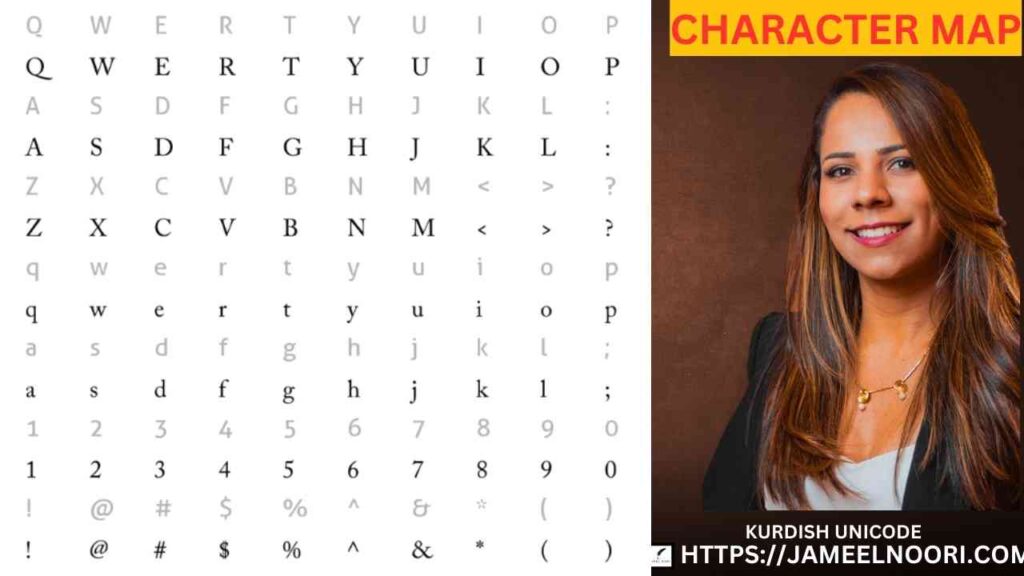
Download Urdu Font Kurdish Unicode – Ultimate Free Guide
Agar aap Urdu ya Kurdish language me type karna chahte hain to Download Urdu Font Kurdish Unicode ek behtareen choice hai. Ye ek TrueType Font hai jo simple installation ke baad aapke computer ya mobile par easily kaam karta hai. Pakistan me kai graphic designers, calligraphers, aur students is font ka use karte hain taake unki Urdu aur Kurdish writing stylish aur readable ho.
Download Urdu Font Kurdish Unicode – Features & Benefits
Download Urdu Font Kurdish Unicode ke kuch khas features hain jo isay popular banate hain:
- Clear & Stylish Design – Urdu aur Kurdish dono languages me readable.
- Professional Look – Publishing, graphics, aur books me use hota hai.
Download Urdu Font Kurdish Unicode – Why It’s Best for Pakistan Users
Pakistan me kai log Arabic script-based fonts prefer karte hain, lekin Download Urdu Font Kurdish Unicode apni clarity aur stylish look ki wajah se alag pehchaan rakhta hai. Iska lightweight design slow computers par bhi smooth performance deta hai, jo khas taur par Lahore, Karachi aur Islamabad ke design studios me pasand kiya jata hai.
Download Urdu Font Kurdish Unicode – Conclusion
Agar aap Urdu aur Kurdish dono me professional typography chahte hain, to Download Urdu Font Kurdish Unicode ek perfect solution hai. Iska design, compatibility aur easy installation isay beginners aur professionals dono ke liye best choice banata hai.
Is Kurdish Unicode a stylish or calligraphy font?
Yes, it has a clean yet stylish design suitable for both professional and artistic work.
Can Kurdish Unicode be used for printing and publishing?
Yes, it is widely used in printing, publishing, and digital graphic design projects.